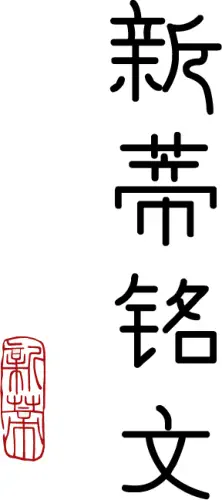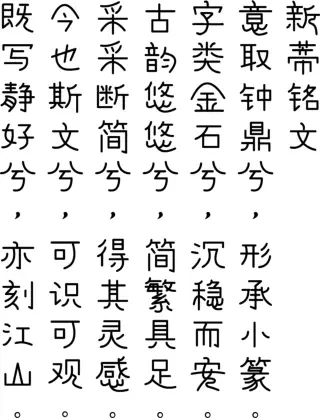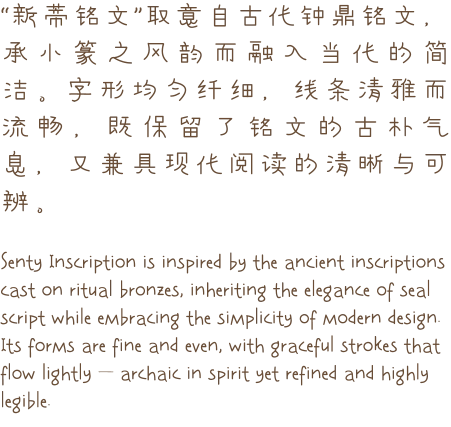
“新蒂铭文”取意自古代钟鼎铭文,承小篆之风韵而融入当代的简洁。字形均匀纤细,线条清雅而流畅,既保留了铭文的古朴气息,又兼具现代阅读的清晰与可辨。  Senty Inscription is inspired by the ancient inscriptions cast on ritual bronzes, inheriting the elegance of seal script while embracing the simplicity of modern design. Its forms are fine and even, with graceful strokes that flow lightly — archaic in spirit yet refined and highly legible.